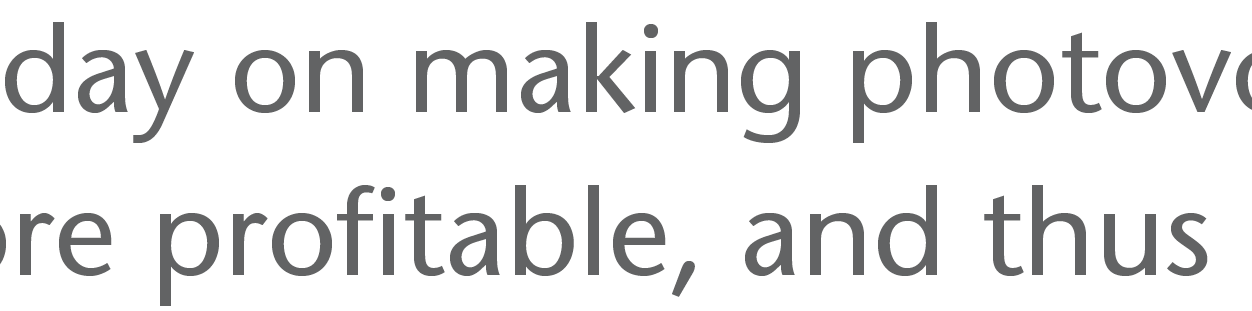
ITC Stone Sans – läuft die immer so weit?
Oder ist da was an meinen Einstellungen faul? Irgendwie sieht das seltsam aus … InDesign CS4, Kerning Metrisch, Laufweite 0.
Und noch eine zweite Frage: Wann soll beim Kerning "Metrisch" und wann soll "Optisch" verwendet werden?
Hallo Bertel,
das läuft bei mir in Quark 7.5 genauso weit. Habs extra in Quark probiert, um auszuschließen, dass es an InDesign liegt.
Und noch eine zweite Frage: Wann soll beim Kerning "Metrisch" und wann soll "Optisch" verwendet werden?
Wenn mich mein Gedächtnis nicht trügt, dann ist »metrisch« die Information, welche im Font selber enthalten ist, wohingegen InDesign bei der Option »optisch« selber versucht, die Abstände auszugleichen. Das funktioniert meiner Erfahrung nach selten gut, oftmals hingegen schlechter als das metrische Kerning.
Damit ergibt sich fast automatisch, daß man a) bei nahezu jedem Font beide Optionen ausprobieren kann/muß, daß man aber bei Zeitmangel b) mit der Option »metrisch« im Regelfall besser fährt als mit »optisch«. Bei freien Fonts ohne anständige Zurichtung habe ich »optisch« schon mit gutem Erfolg eingesetzt, bei qualitativ hochwertigeren Fonts probiere ich es, wenn überhaupt, nur bei größeren Schriftgrößen, quasi als Ausgangspunkt für händische Nacharbeit.
Ich arbeite fast immer mit metrischem Kerning. Lediglich bei bei Headlines teste ich hin und wieder das optische Kerning und ab und an passt es tatsächlich besser als das metrische (was aber auch an schlecht »gekernten« Schriften liegen kann) ...
Hallo Bertel, das läuft bei mir in Quark 7.5 genauso weit. Habs extra in Quark probiert, um auszuschließen, dass es an InDesign liegt. Gruß, Kathrin :D
Da bedanke ich mich ganz artig :D Schade dass der Font in Displaygrößen so schlecht funktioniert, er muss aber leider auch so eingesetzt werden. Naja, werd ich den Text halt wieder mal von Hand hinfrickeln.
Wenn mich mein Gedächtnis nicht trügt, dann ist »metrisch« die Information, welche im Font selber enthalten ist, wohingegen InDesign bei der Option »optisch« selber versucht, die Abstände auszugleichen. Das funktioniert meiner Erfahrung nach selten gut, oftmals hingegen schlechter als das metrische Kerning.
Damit ergibt sich fast automatisch, daß man a) bei nahezu jedem Font beide Optionen ausprobieren kann/muß, daß man aber bei Zeitmangel b) mit der Option »metrisch« im Regelfall besser fährt als mit »optisch«. Bei freien Fonts ohne anständige Zurichtung habe ich »optisch« schon mit gutem Erfolg eingesetzt, bei qualitativ hochwertigeren Fonts probiere ich es, wenn überhaupt, nur bei größeren Schriftgrößen, quasi als Ausgangspunkt für händische Nacharbeit. Grüße, Christian
So hab ich das auch im Kopf und so handhabe ich das auch ständig. Gut, dass ich da Bestätigung finde, ich war etwas verwirrt, weil die Stone so arg störrisch ist.
Bei Schriften mit ausschließlich Tabellenziffern, kann man im Fliesstext mit der Einstellung optisch ausgewogenere Ziffernabstände hinbekommen, ohne jede Ziffer händisch spationieren zu müssen.